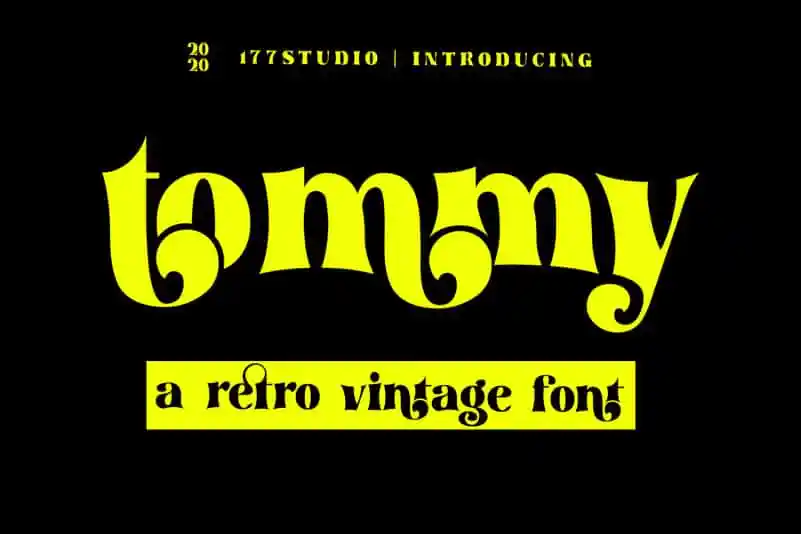
Tommy – Retro Serif Font – Download Grátis
A Tommy – Retro Serif Font é uma elegante escolha para aqueles que buscam um touch nostálgico em seus projetos digitais. Esta nova serif incorpora um sans-serif extra, criando combinações perfeitas e mantendo o charme da estética retro de forma moderna e atemporal. Desenvolvida pelo designer 177Studio, Tommy é uma opção ideal para designers que valorizam a fusão dos estilos serif e sans-serif na sua paleta de fontes. Este novo design oferece um estilo vintage combinado com uma forte presença visual, perfeitamente adaptada para manter a consistência em projetos tanto modernos quanto clássicos. Para quem busca dar vida à sua ideia através de textos, Tommy é certamente um investimento valioso na sua coleção de fontes.